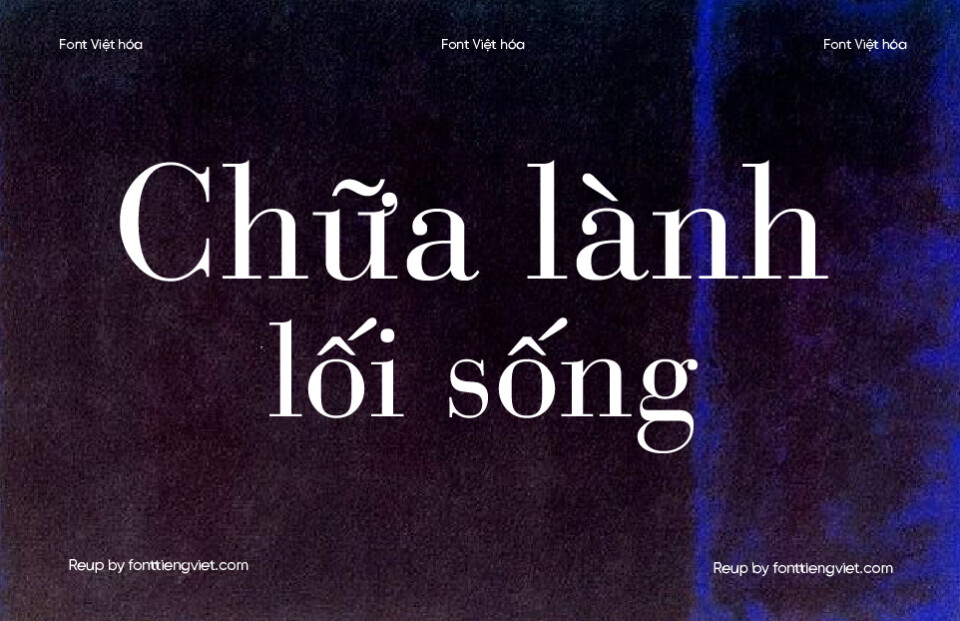
Trong thế giới thiết kế đồ họa và xuất bản, việc lựa chọn Font Chữ đóng vai trò then chốt, quyết định đến tính thẩm mỹ và khả năng truyền tải thông điệp của tác phẩm. Đặc biệt, đối với các ấn phẩm học thuật, báo cáo chuyên nghiệp hay luận văn tốt nghiệp, một phông chữ chất lượng cao, dễ đọc là điều không thể thiếu. Hôm nay, chúng ta sẽ đi sâu vào tìm hiểu một tuyệt phẩm typography được giới chuyên môn đánh giá cao: Font Việt hóa UTM Bauer Bodoni. Đây không chỉ là một phông chữ đẹp mà còn là sự kết hợp hoàn hảo giữa nét cổ điển tinh tế và khả năng hiển thị tiếng Việt tối ưu, giúp nâng tầm mọi dự án của bạn.
UTM Bauer Bodoni: Dòng Font Chữ Kinh Điển và Lịch Sử Ra Đời
Dòng font Bauer Bodoni gốc được thiết kế dựa trên các tác phẩm của Giambattista Bodoni, một thợ in nổi tiếng người Ý thế kỷ 18. Bộ font này thuộc nhóm Didone, đặc trưng bởi độ tương phản rất cao giữa các nét dày và nét mỏng, tạo nên vẻ ngoài thanh lịch, sang trọng và đầy uy quyền. Sự ra đời của Bauer Bodoni đánh dấu một bước tiến quan trọng trong lịch sử typography, trở thành chuẩn mực cho sự tinh tế trong thiết kế sách và tạp chí cao cấp.
Khi du nhập vào Việt Nam, để đáp ứng nhu cầu sử dụng rộng rãi, các nhà phát triển font chữ đã tiến hành Việt hóa bộ Bauer Bodoni. Quá trình này không chỉ thêm các dấu tiếng Việt một cách hài hòa mà còn tối ưu hóa khoảng cách và kerning (khoảng cách giữa các ký tự), đảm bảo văn bản tiếng Việt vẫn giữ được sự cân đối và dễ đọc vốn có của phông chữ gốc. Đây chính là lý do các nhà thiết kế luôn tìm kiếm bộ Font Việt hóa chất lượng như UTM Bauer Bodoni.
Đặc Điểm Nổi Bật Của Bộ Font UTM Bauer Bodoni
Font chữ Bauer Bodoni nổi bật với một số đặc điểm nhận dạng rõ rệt. Thứ nhất là các serifs (chân chữ) rất mỏng, dứt khoát và gần như ngang tuyệt đối, khác biệt hoàn toàn so với các font serif cổ điển hơn. Thứ hai là sự tương phản mạnh mẽ giữa các nét chính (dày) và các nét phụ (mỏng), tạo cảm giác sắc nét và hiện đại dù mang phong cách cổ điển. Thứ ba, phiên bản UTM Việt hóa được chăm chút kỹ lưỡng về các ký tự có dấu, đảm bảo tính nhất quán và chuyên nghiệp khi sử dụng cho các tài liệu học tập, sách giáo khoa hay các ấn phẩm yêu cầu độ trang trọng cao.
Lợi Ích Của Việc Sử Dụng Font Việt hóa UTM Bauer Bodoni Trong Thiết Kế
Việc sử dụng Font Việt hóa UTM Bauer Bodoni mang lại nhiều lợi ích thiết thực, đặc biệt trong môi trường học thuật và xuất bản. Với độ tương phản cao, phông chữ này giúp văn bản in ấn trở nên rõ ràng, dễ đọc, giảm mệt mỏi thị giác cho người đọc, điều rất quan trọng đối với học sinh, sinh viên phải đọc tài liệu kéo dài. Trong lĩnh vực thiết kế thương hiệu, nó truyền tải sự cao cấp, uy tín và sự tinh tế, phù hợp cho các nhãn hàng thời trang, mỹ phẩm hoặc các dịch vụ tài chính cao cấp.
Đối với học sinh cấp ba đang chuẩn bị cho các kỳ thi tốt nghiệp quan trọng, hay sinh viên đại học làm luận văn, việc trình bày tài liệu bằng một phông chữ chuyên nghiệp như UTM Bauer Bodoni sẽ tạo ấn tượng tốt hơn về mặt hình thức. Nó thể hiện sự đầu tư nghiêm túc vào sản phẩm, từ đó nâng cao chất lượng tổng thể của bài làm. Hơn nữa, font chữ này đã được tối ưu hóa đầy đủ cho tiếng Việt, loại bỏ hoàn toàn nỗi lo về lỗi font hay thiếu dấu tiếng Việt thường gặp ở các phiên bản quốc tế.
Ứng Dụng Thực Tế Cho Học Sinh, Sinh Viên và Thiết Kế Ấn Phẩm
- Tài liệu học tập và báo cáo: Tạo ra các tài liệu in ấn sắc nét, dễ đọc cho các bài giảng, tóm tắt kiến thức.
- Luận văn và khóa luận: Đảm bảo tính trang trọng và chuyên nghiệp cho các công trình nghiên cứu khoa học.
- Thiết kế tạp chí và sách: Mang lại vẻ đẹp thanh lịch, cổ điển cho các ấn phẩm văn hóa nghệ thuật.
- Bộ nhận diện thương hiệu: Thích hợp cho logo và tiêu đề (headline) của các thương hiệu muốn thể hiện sự sang trọng và lịch sử.
Tóm lại, Font Việt hóa UTM Bauer Bodoni là một sự lựa chọn tuyệt vời cho bất kỳ ai đang tìm kiếm một phông chữ vừa mang tính thẩm mỹ cao, vừa đảm bảo tính chuyên nghiệp và khả năng hiển thị tiếng Việt hoàn hảo. Từ các bài kiểm tra quan trọng của học sinh, các dự án thiết kế đồ họa phức tạp, đến những ấn phẩm cao cấp, sự thanh lịch và độ tương phản của Bauer Bodoni luôn mang lại giá trị vượt trội. Hãy đảm bảo rằng bạn đã thêm bộ Font Chữ kinh điển này vào bộ sưu tập của mình để nâng cao chất lượng sản phẩm. Đầu tư vào phông chữ chính là đầu tư vào sự chuyên nghiệp và uy tín của bản thân.